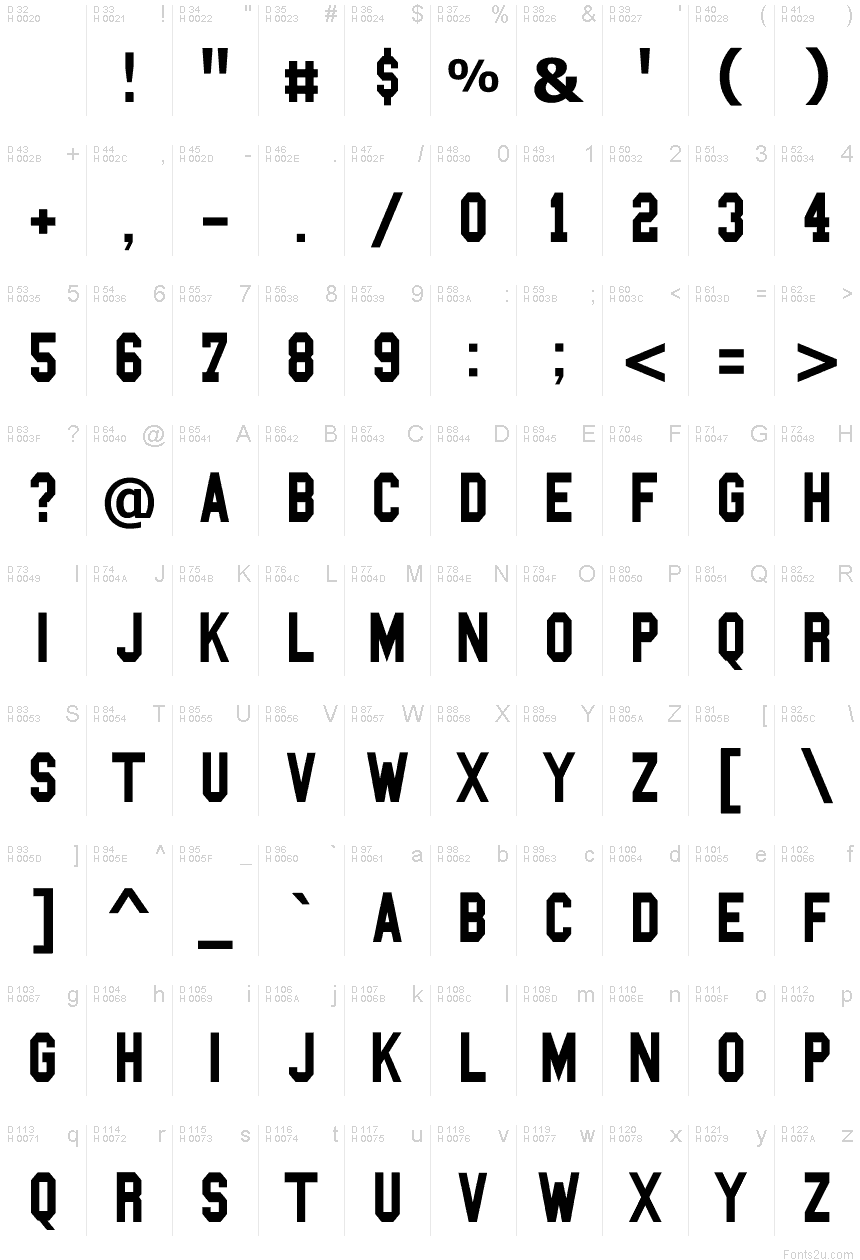
Blockbusted من تصميم Dennis Ludlow هو خط عرض (display font) مجاني بطابع تقني عسكري، يتميز بوزن وحضور الفولاذ المشغول. أشكاله الضخمة والمربعة ووقفته الضيقة والمستقيمة تشعرك وكأنها علامات بارزة على المركبات المدرعة أو أجهزة الألعاب القديمة (أركيد). تتشابك الحروف كأنها كتل معيارية، مما يمنح العناوين مظهراً كثيفاً ومحصناً يسهل قراءته فوراً حتى من مسافة بعيدة. الزوايا الداخلية الحادة والهندسة الصارمة تضفي لمسة صناعية قاسية دون التضحية بالوضوح.
يتألق هذا الخط المجاني Blockbusted في شعارات الألعاب، وهويات الرياضات الإلكترونية، وملصقات الخيال العلمي، ورسومات الفعاليات التقنية، وتغليف الطائرات بدون طيار أو المعدات، والصور المصغرة الجريئة على يوتيوب. تخلق العروض الموحدة إيقاعاً قوياً ومنتظماً يحول الكلمات القصيرة إلى شارات نصية صلبة. لتحقيق أقصى تأثير، استخدمه بحجم كبير وبأحرف كبيرة (كابيتال)، ثم ادمجه مع خط بلا زوائد (sans serif) نظيف وخفيف للعناوين الفرعية أو نصوص الواجهة لموازنة طابعه الميكانيكي الثقيل.